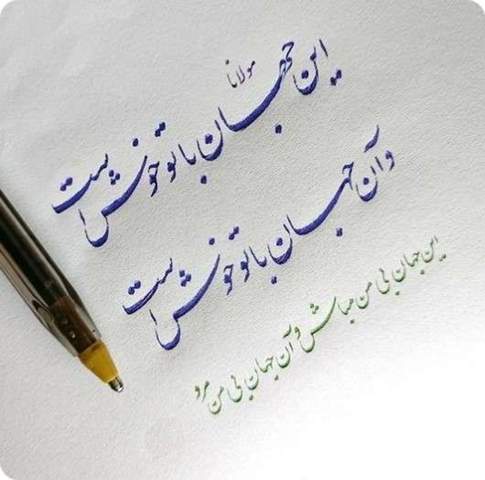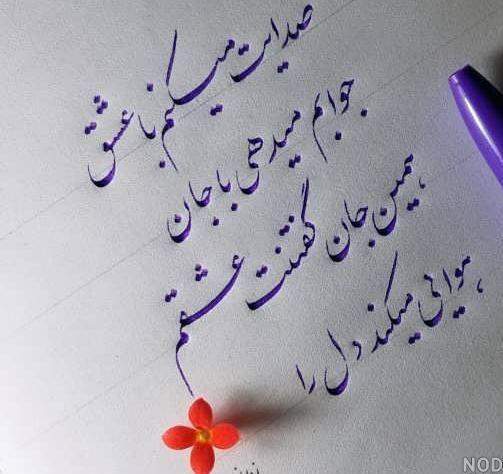
Wie findest du diese Schriftart?
Persisch
Sehr schön! Und das sagt dir eine Schriftsetzerin.
Ich liebe Nasta‘liq, so der Name dieser wunderschönen und eleganten arabischen Schriftart!
Araber nennen sie auch einfach khatt al-farisiy, persische Schrift(kunst). Diese Schrift wird von der Persern besonders gern für Poesie verwendet. Es gibt auch Bücher mit Gedichten in dieser Schrift. Zu Hause habe ich eine Ausgabe von Saadis Golestan (Rosengarten) in dieser Schrift.
In Nasta‘liq werden in Pakistan und Indien sogar Tageszeitungen gedruckt, wie hier die Zeitung Express, Ausgabe von Islamabad https://iqbalforum.org/news/1506/
Und hier noch „etwas“ mehr:
Mit persichen Fonts kenne ich mich nicht so aus, aber sieht ziemlich clean aus
Finde ich sehr schön.
Auf deutsch: Diese Handschrift ist künstlerisch und elegant. Die normale persische Handschrift ist einfacher (so).
Ja, das ist zumeist Shekasteh, was etwa „gebrochene“ bedeutet, die aber aus Nasta‘liq entstanden ist. Da gibts auch künstlerische Formen wie auch schlichte für den Alltag.
Ich verstehe kein Wort, aber ich mag das Aussehen, die Ähstetic
Dieser Kunststil ist auf persisch etwas normaler, mein Freund.
این دست خط هنری و نستعلیق است. دست خط فارسی معمولی ساده تر است(اینگونه)😁😁